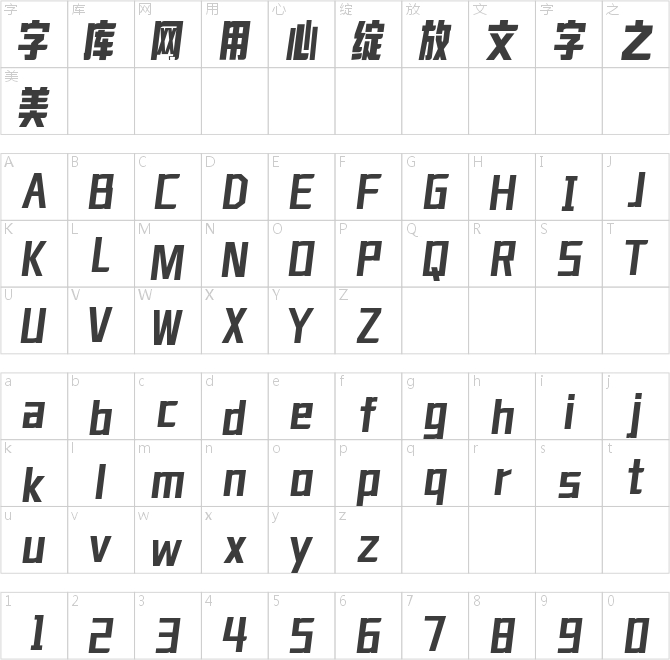
字魂創(chuàng)想概念體
字魂創(chuàng)想概念體字體字庫(kù)是一款讓人賞心悅目、百看不厭的中文字體,適合各類(lèi)廣告和產(chǎn)品包裝設(shè)計(jì)應(yīng)用,字體大小1.64MB,格式為ttf字體,上傳用戶(hù)是那是不變的,作者/版權(quán)方為字魂